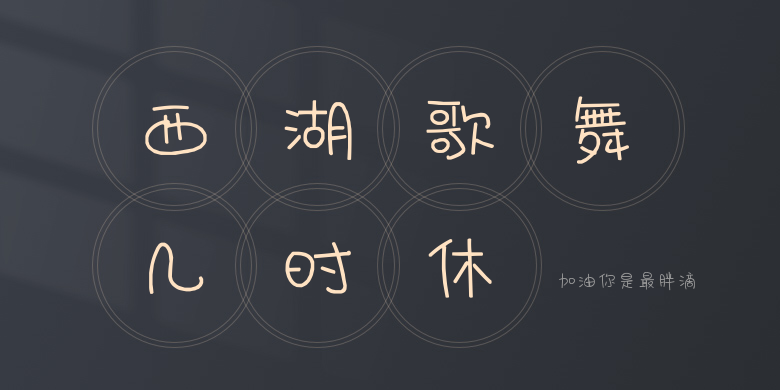
加油你是最胖滴
加油你是最胖滴,这款字体结构工整、笔画清晰,兼顾美观与易读性,适用于标题、正文、海报、包装、LOGO 等多种场景。字形优雅稳定,风格百搭耐看,适配日常排版与创意设计,让文字呈现更舒适、更具质感。加油你是最胖滴一笔一画,皆是细节,以均衡的比例、流畅的线条打造舒适视觉体验,字形端正大气,风格简约现代。无论是商业设计、品牌宣传还是日常排版,都能轻松驾驭,让文字更有格调与力量。加油你是最胖滴字体下载。